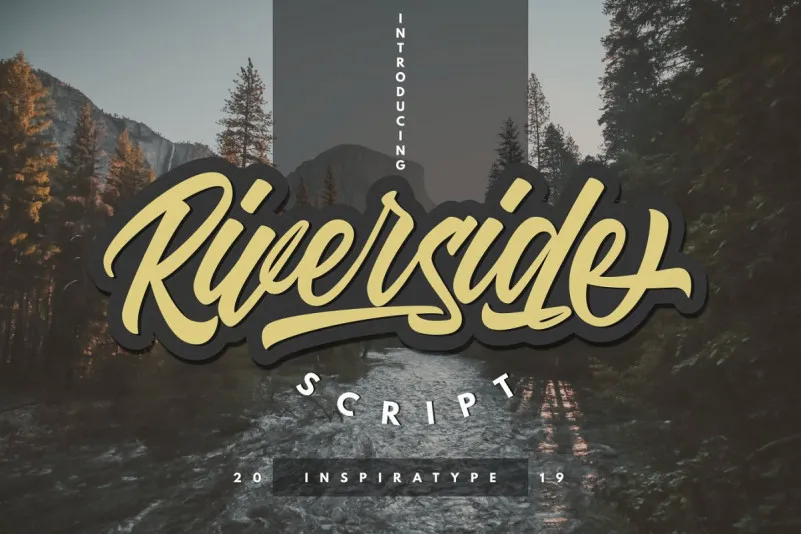
A Riverside Script Font é uma excelente escolha para qualquer projeto que deseje um estilo elegante e sofisticado. Inspirada nas antiguas cartazes clássicos, esta fonte está especialmente concebida para ambientes de display, oferecendo um toque retrô e artístico aos seus designs. Ela traz não apenas letras maiúsculas e minúsculas, mas também números e sinais de pontuação, com uma variedade infinita de alternativas do OpenType, ligaturas padrão e até mesmo swashes adicionais. Este conjunto impressionante de recursos permite que você personalize seu design conforme necessário, seja para logotipos, cartões de carta, panfletos ou até mesmo rótulos de embalagens. Além disso, a Riverside Script Font tem uma capacidade única de transformar seus projetos em verdadeiras obras de arte. Perfeita tanto para o trabalho diário quanto para projetos especiais, ela se destacará em qualquer aplicação onde um estilo singular seja desejado. Seja através do seu uso em logotipos, cartões de carta personalizados ou até mesmo na criação de rótulos customizados, a Riverside Script Font fornecerá o toque perfeito para seus trabalhos.